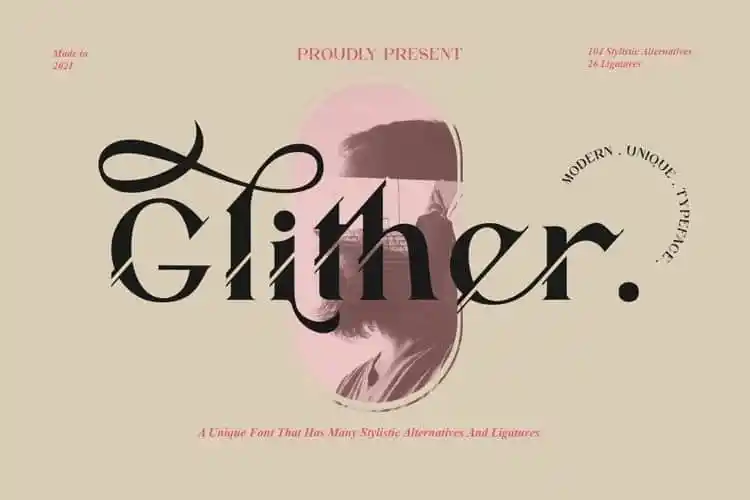
A Glither Serif Font é uma tipografia serifada para uso em títulos e elementos visuais de destaque projetada por Alit Suarnegara. Com ligaturas perfeitas e suporte a múltiplas línguas, essa fonte apresenta um conceito elegante e forte. Perfeitamente adequada para designs que exploram temas tecnológicos como conceitos modernos e citações. Com sua tipografia serifada em linha reta, a Glither Serif oferece uma combinação perfeita de simplicidade e estilo. Suas ligaturas completas permitem um texto fluido e profissional, ideal para títulos ou qualquer elemento visual onde deseja-se chamar atenção. Como uma fonte com suporte multilíngue, é adequada para usar em qualquer projeto que exija um design impecável, desde letras de destaque até textos internos. Para designers que buscam um toque único e moderno em suas criações visuais, a Glither Serif Font é uma escolha inteligente. Perfeito tanto para estilos tradicionais quanto para aqueles com temas tecnológicos, essa fonte oferece uma experiência visual envolvente e profissional.